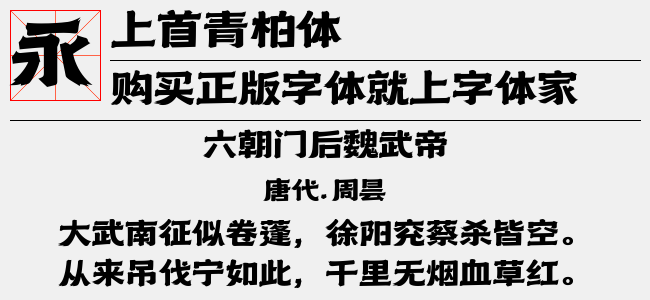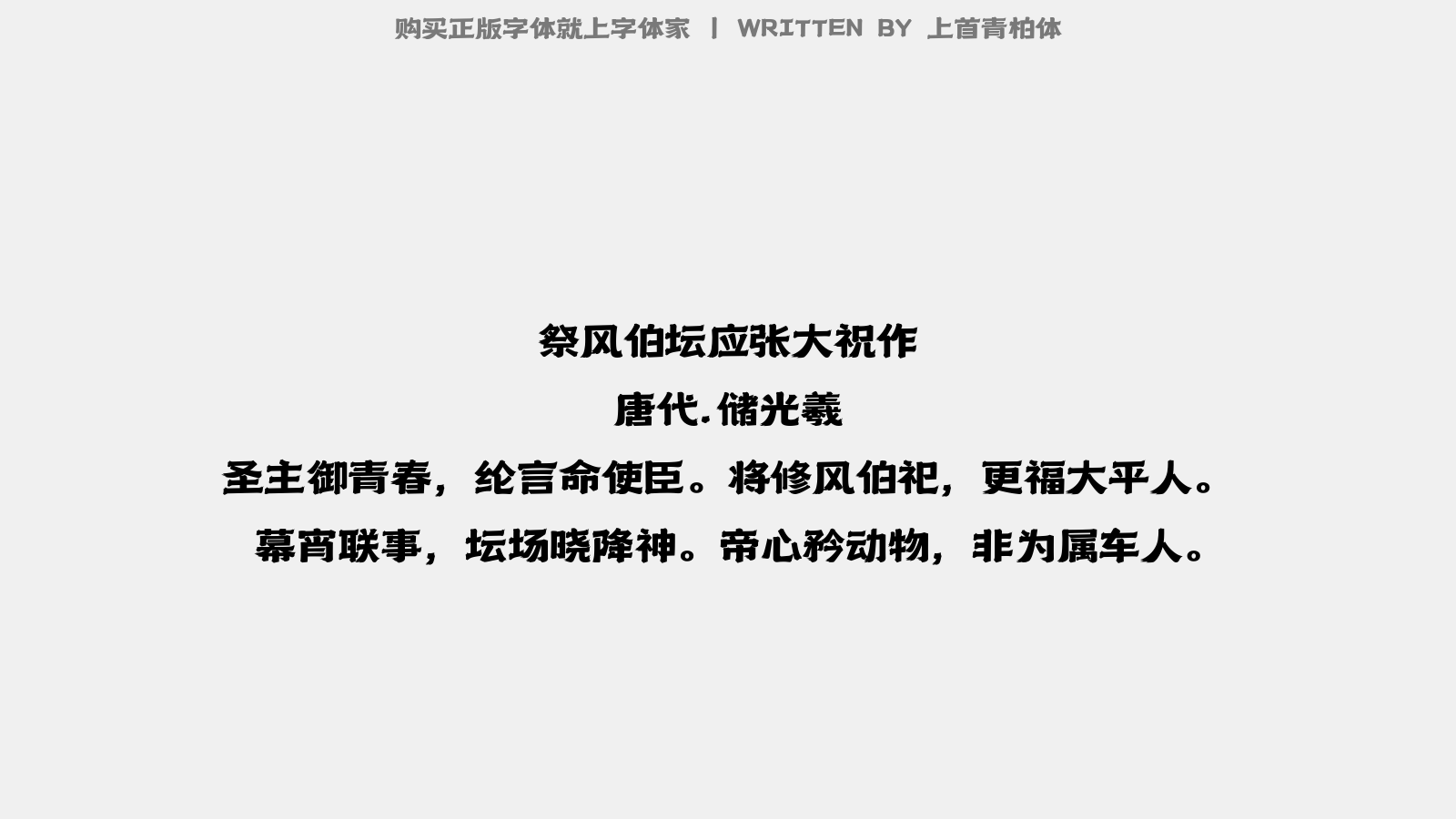
上首青柏体
字体作者:上首造字
字体名称:上首青柏体
书体类型:手写/印刷类
字体公司:上首造字
上首青柏体
上首青柏体,简体中文约6763字,字体整体以黑体为框架,将一些原始的元素融合进字体,而字体笔画粗细均匀,整体方正有力,使字体在拥有原始野性力量的同时又不失现代字体的简洁大方。字体整体符合现代潮流又拥有原始韵味,适用于搭配标志、广告标语、商业广告、海报字体等高端属性。